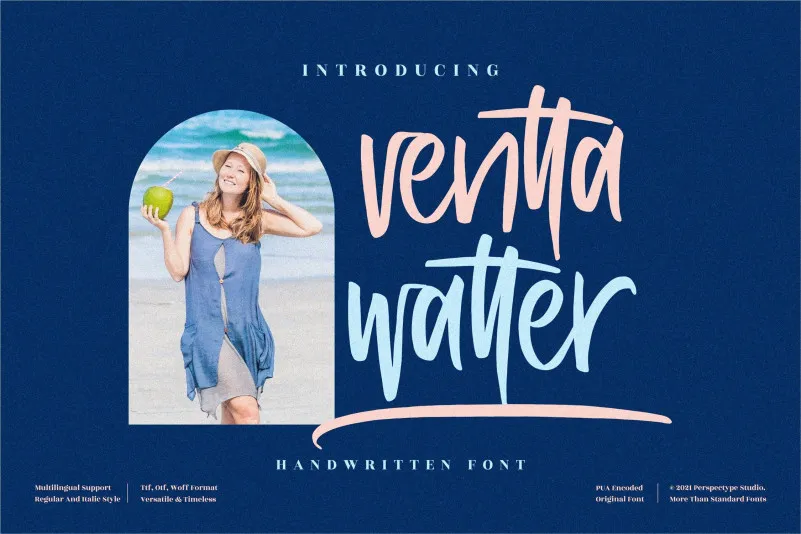
Ventta Watter Font – Download Grátis
A ‘Ventta Watter Font’ é uma elegante escolha para aqueles que buscam uma fonte casual e descontraída. Como um script font, esta opção apresenta um estilo de escrita agradável e despojada, perfeitamente adequado tanto para uso em textos informais quanto em criações mais elaboradas. Esta fonte é não apenas versátil, mas também funcional, tornando-a uma ótima adição ao seu catálogo de fonts. Perfeita tanto para mensagens pessoais quanto para elementos gráficos, a ‘Ventta Watter Font’ tem o poder de transformar qualquer projeto em um verdadeiro ativo de design. Seja você designer de sites ou criador de publicações digitais, este é o tipo de font que vai fazer sua marca soar autêntica e única.